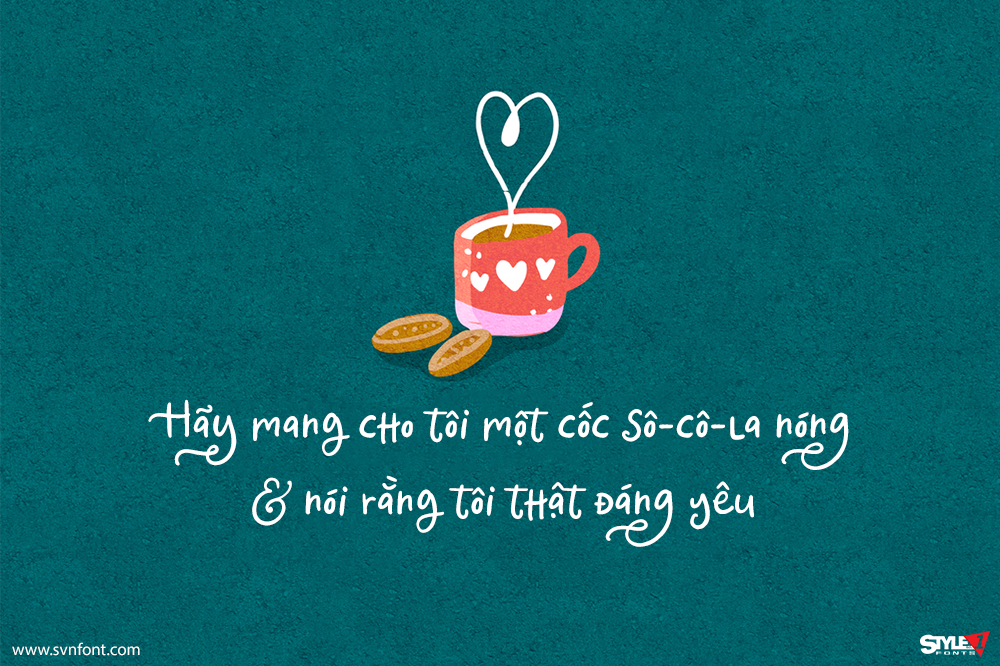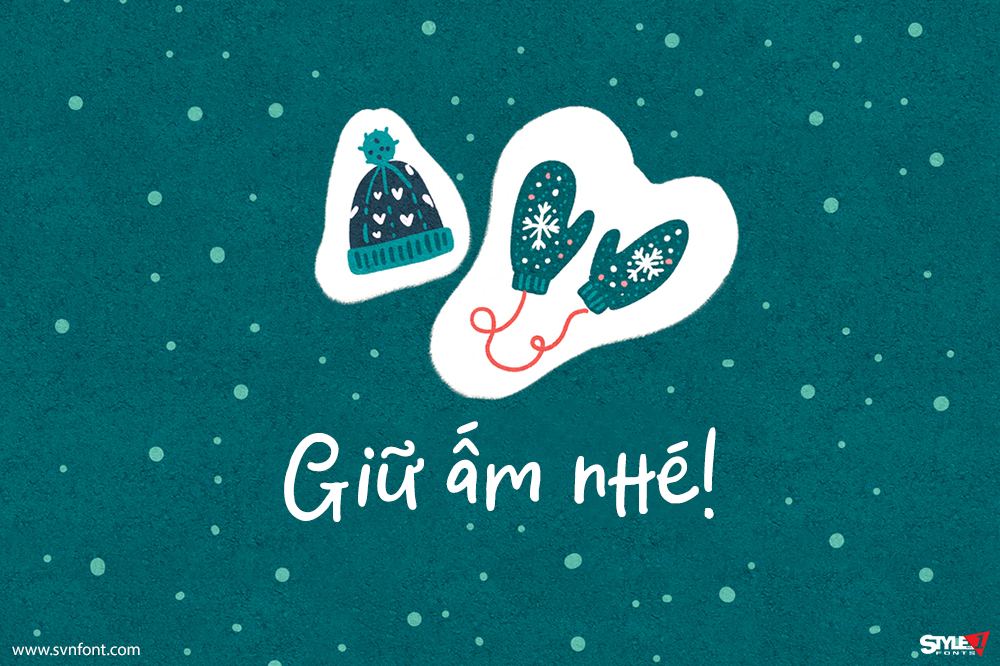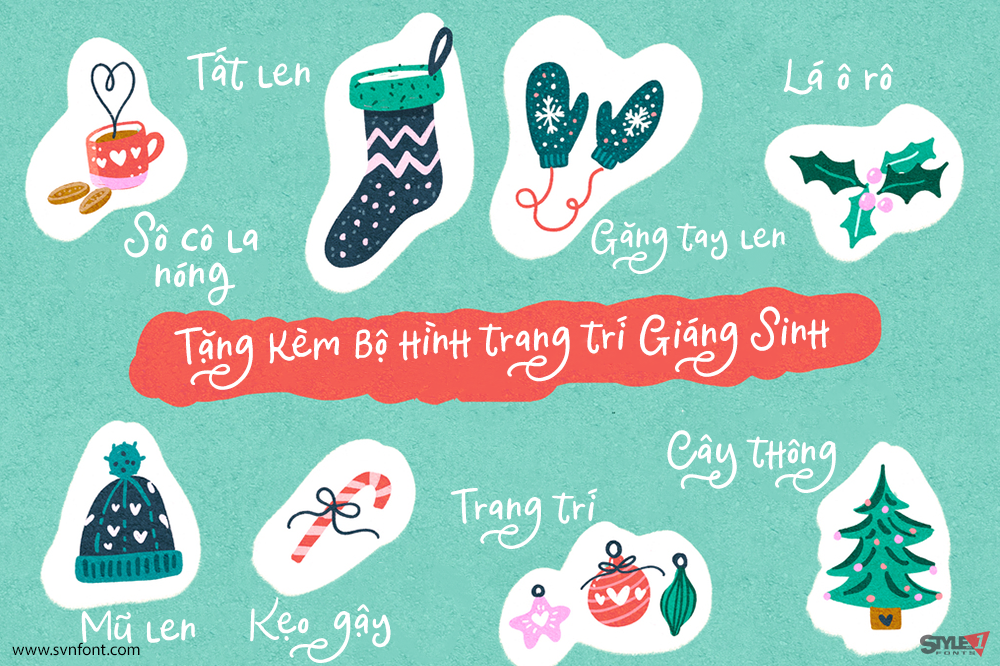
Vừa kịp lúc để chuẩn bị cho mùa Giáng Sinh! Nếu bạn đang tìm một font chữ Giáng Sinh nhỏ xinh và dễ thương thì không cần tìm đâu xa nữa! Sticky Toffee Pudding là một font chữ vui nhộn với rất nhiều nét uốn lượn và xoắn cong ngọt ngào 🙂 Font có sẵn các ligature tích hợp và một vài ký tự thay thế để tăng thêm sự thú vị!
Nhà thiết kế: Nicky Laatz
Nhà phát hành: Nicky Laatz